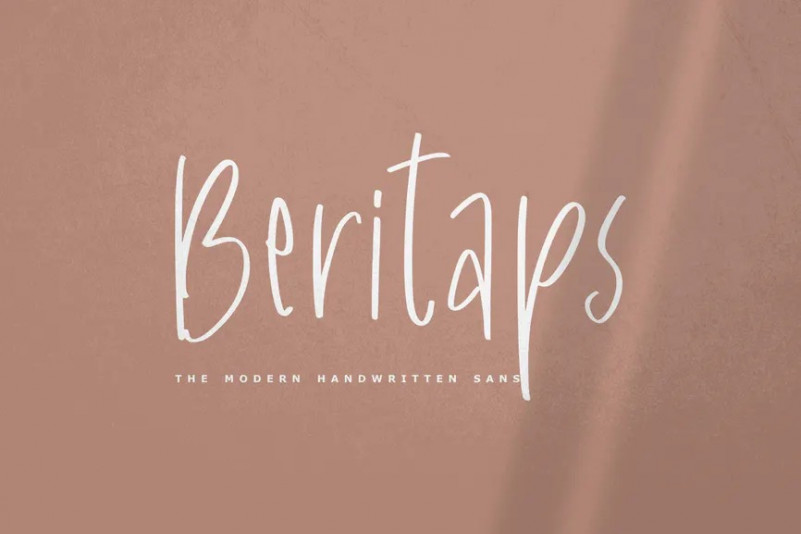
Beritaps Font
Beritaps – La police manuscrite
Un écriture manuscrite et un caractère unique ! Il est parfait pour les Logos, les cartes nominatives, les mises en page de magazines, les invitations, les en-têtes ou même les œuvres d’art à grande échelle.